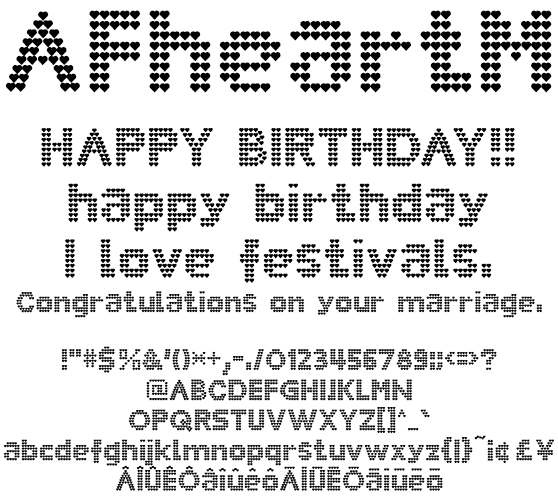
ハート欧文 AFheartM
AFheartM
発売中の AFSGirly21Font (ガーリー系21書体フォントセット) に含まれる AFSfunnyHeart.ttf より収録文字を増やし、少々太めなイメージに仕上げました。デザインパーティーやお誕生日の案内などお洒落なドキュメントに最適。個人同人向けアニメ、動画向けなフォントです。